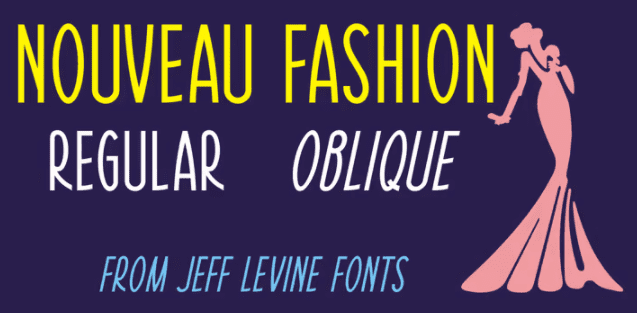
На нотной обложке песни "You Brought A New Kind of Love to Me" в стиле модерн имеется приятный заголовок с ручной надписью. Песня звучит в фильме компании Paramount 1930 года "Большой пруд" с участием Мориса Шевалье и Клодетт Кольбер.
Оригинальная надпись была сделана пером ручки с круглым наконечником и имела множество мелких неточностей. Для цифровой версии он был немного "подтянут" и теперь доступен как Nouveau Fashion JNL, в обычном и наклонном вариантах.